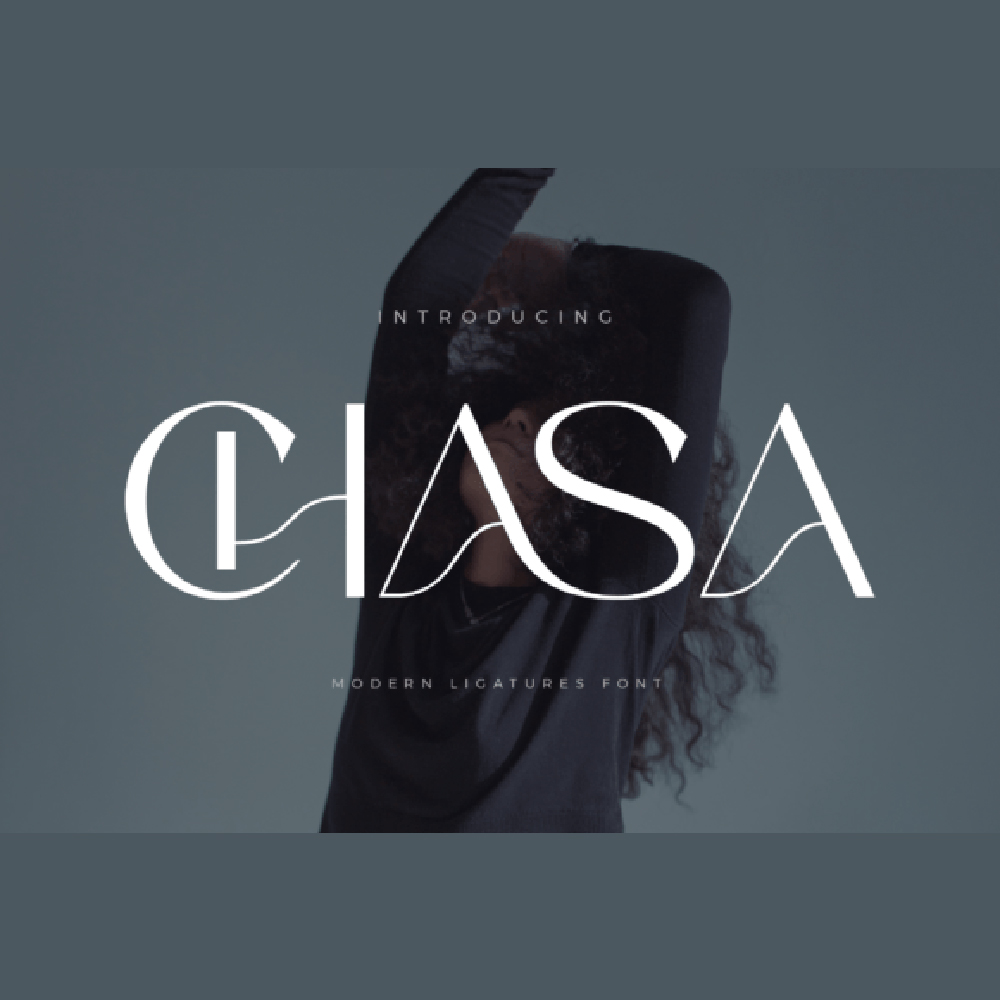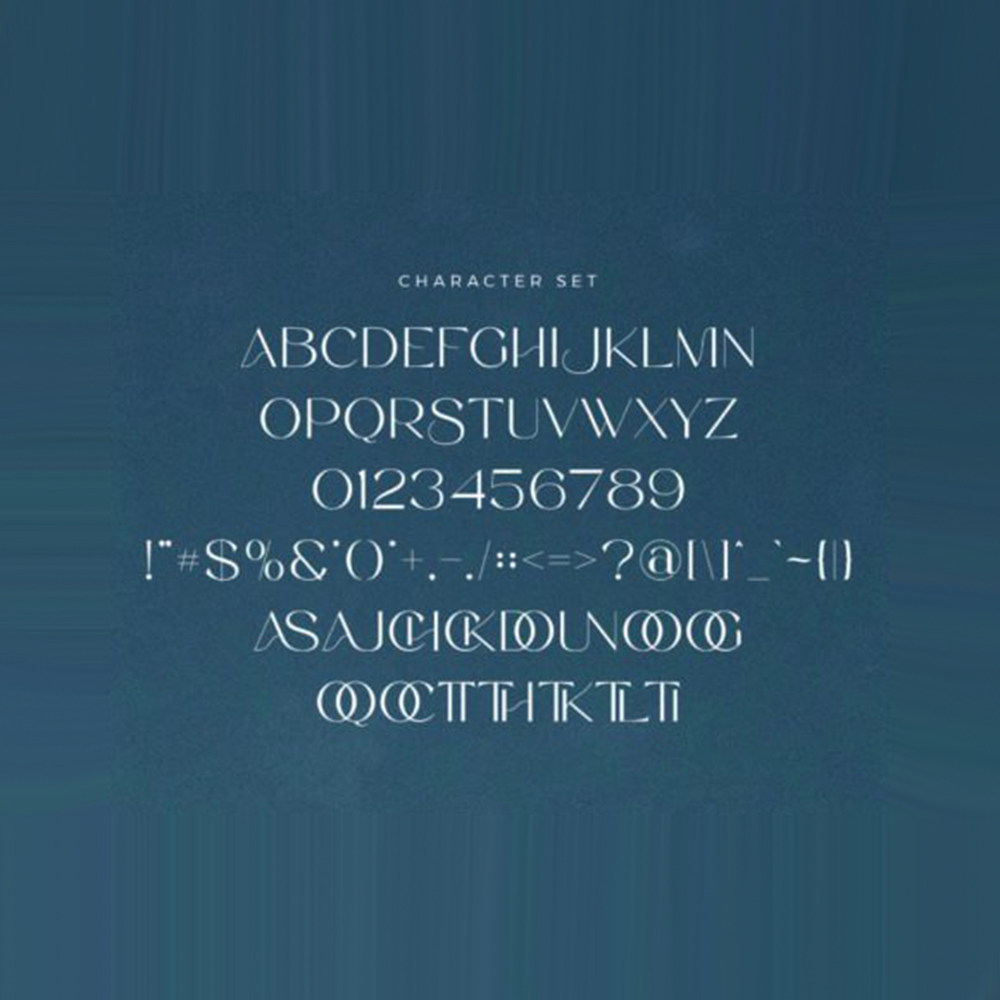
فونت پرمیوم و انگلیسی Chasa Font یک فونت سنس سریف است که با الهام از لوگوی معروف مینیمالیستی ساخته شده و برای اهداف طراحی قالب، بروشور، ویدیو، برندسازی تبلیغاتی، لوگو، دعوتنامه، طراحی چیدمان، صنایع دستی زیبا، طراحی زیبایی و موارد دیگر ایدهآل است.